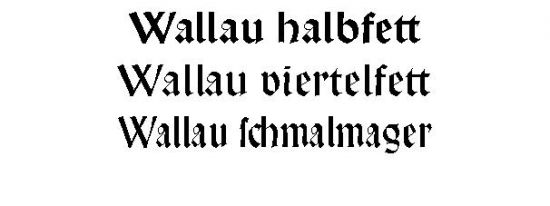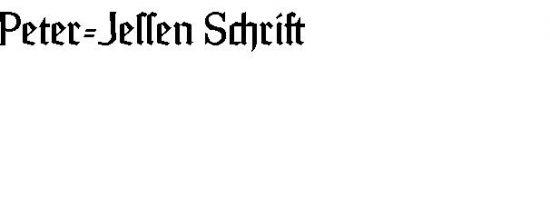
Hilfe benötigt: Schrift für Taufprogramm
Meine Tochter soll demnächst getauft werden und nun suche ich eine passende Schrift zur Gestaltung eines Programmheftes für den Gottesdienst. Genauer gesagt suche ich 2 Schriften: 1 für die Überschriften und 1 für den Text.
P.S.: Was würdet ihr von der LT Wiesbaden Swing halten für die Überschriften?
@Schweizerdegen: Wäre dann als Ergänzung zur Wiesbaden in den Überschriften z.B. die Frutiger denkbar? Ich bin ein ziemlicher Typo-Laie, aber diese Schrift ist doch meines Wissens klar, gradlinig, oder?
Zapfino fänd' ich noch feierlicher, wenn's eher klassisch sein soll. Und dann eher mit einer Antiqua (Minion?) kombiniert, das strahlt im Text mehr Ruhe aus als eine Grotesk (finde ich zumindest).
Ich sehe tatsächlich häufig folgendes Problem, hier am Beispiel der Taufkarte:
Jemand fragt nach einer Schrift-Empfehlung.
Darauf bekommt er ein halbes Dutzend Antworten mit insgesamt drei Dutzend Links zu sehr konkreten Schriften oder den Namen dieser Schriften. Und das oft unkommentiert.
Was mir persönlich besser gefällt, sind konkrete Begründungen oder kurze, elektronisch erstellte Abbildungen. Aber es mag sein, daß das den Rahmen sprengt.
Hmmja, da haben der Schweizer-Martin und der Blei-Georg recht. Es wär tatsächlich gscheiter mal was zu basteln und dann mal die Horde drüber zu lassen. Aber: Genau das ist es ja. ICH möchte das eigentlich nicht zur Diskussion stellen, weil das halt - zumindest für mich - eine sehr persönliche Sache darstellt. Und das Ding ja auch schon versendet ist, also nicht mehr geändert werden kann. Also: Kein Bild.
Übrigens die Poetica empfinde ich auch als eine sehr schöne Alternative, aber eben mit einer ganz anderen Anmutung.
[offtopic] Ich hab kurz einmal die Ministry Script in der Auswahl gehabt, aber da stand dann gar zu sehr "Hochzeit" über allem. Hat diese wunderbare Schrift eigentlich nicht verdient. Wunderbares Ligaturen-und Alternatehandling vom Herren Paul. Und da gehts mir leider auch mit der Zapfino so. Wunderbares Ding, leider halt schon so in ein Eck gedrängt. Aber DAS alles ist sowas von subjektiv, dass es eigentlich in ein Blog gehört und nicht hierher ...
Wie wäre es mit einer Rundgotisch?
Oder mit einer schlichten Gotisch, wie der auch für ungeübte Leser geeigneten
Nein, keine Wallau oder Jessen.
Das wäre in den 40er Jahren vielleicht zeitgemäß gewesen, aber nicht jetzt.
Die Schrift muß zart sein, aber klar.
Nicht trutzig, aber stolz.
So was braucht das Kind. Und die Mutter. Und der Vater.
Ich mein ja nur..
@Norbert Pautner: Zapfino ist in der Tat sehr schön klassisch, aber eine Spur zu feierlich, wie ich finde. Was wäre mit einer Kombi aus Minion und Wiesbaden? Denkbar oder Unsinn?
@CHSC: auch die Poetica ist ein guter Tip.
Ich denke, ich werde wirklich mal etwas versuchen und Euch das Ergebnis präsentieren, dann sehen wir weiter. Ist sicher eine gute Vorgehensweise.
Falls jemand aber noch den einen oder anderen Vorschlag hat, kann er diesen natürlich noch gerne hier Kund tun.
ich weiß ja nicht wie ich das jetzt sagen soll, aber: Muss es die WiesbadenSwing denn unbedingt sein? Aus meiner subjektiven Sicht heraus transportiert sie sowas - wie sage ich das jetzt? - supermarkt-preisreduziertes. Das kann sie gut, soll sie auch. Aber ich weiß nicht ob sie jetzt als tragende Schrift auf der Taufeinladung so passend wäre.
Ich denke, du suchst eine digitale Handschrift um die Persönlichkeit zu transportieren. Wenn du nicht zu lange Überschriften hast probier mal die Scriptina von Apostrophic Labs. Ist günstig, verspielt und festlich. Aber funktioniert m.E. nur bei kurzen Worten richtig gut (wegen der hohen Ober- und Unterlängen). Oder aber du nimmst dir einfach ganz klassisch eine Garamond, eine Serifenschrift in passender Umgebung (siehe Schweizermartin) funktioniert oft perfekt.
Aha, hoppla, das habe ich überlesen. Danke für den Input. Aber dann wäre es doch konsequent sich an der Gestaltung der Einladung zur Taufe zu orientieren. Wenn dort die Wiesbaden genommen wurde, dann soll's in Gottes Namen natürlich auch im Programm verwendet werden. (Aber bitte maximal als Headline-Schrift, nicht als Mengentext.)
@Schwalbenkoenig: Ich hatte ohnehin vor, die Wiesbaden nur für die Headlines zu verwenden, da ich sie bei Textblöcken für, sagen wir mal "Suboptimal" halte...